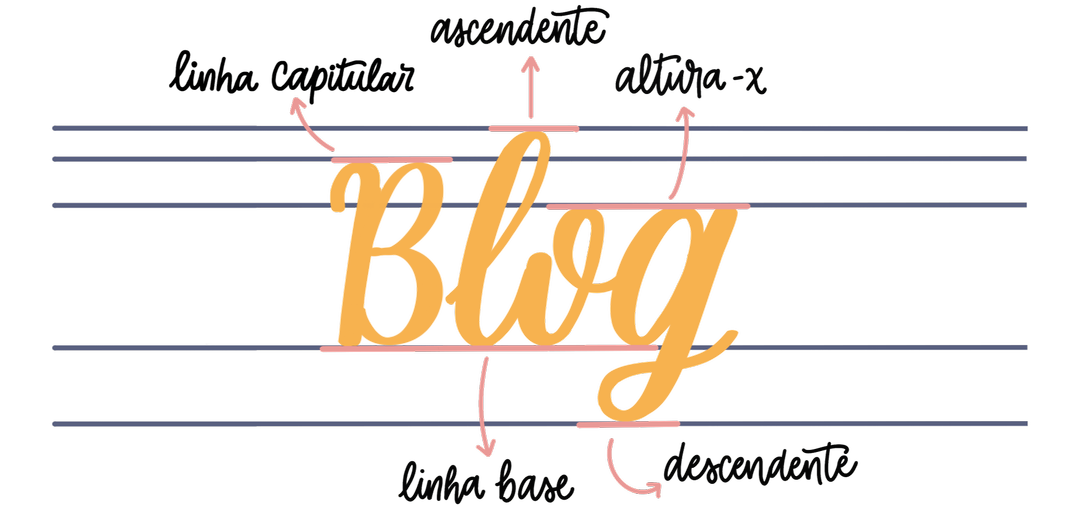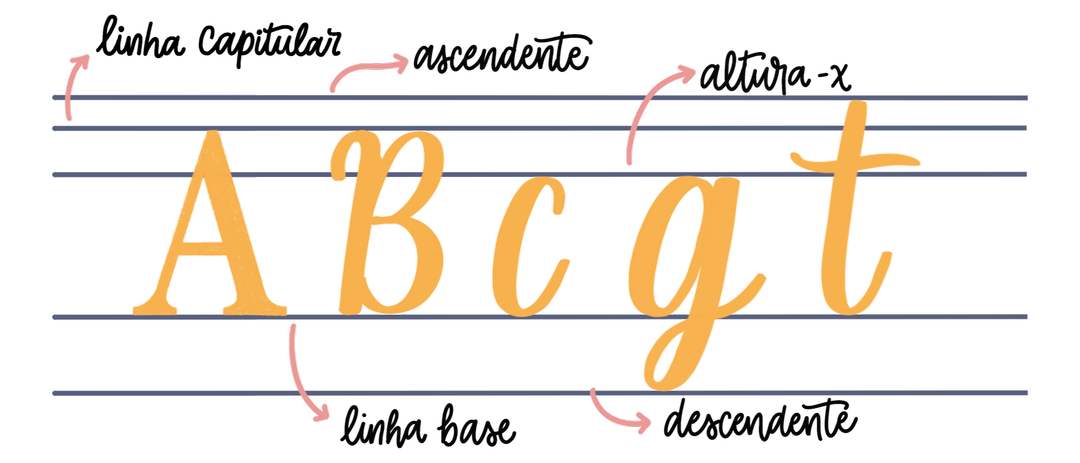
Linhas Guias
Nesse post vamos falar sobre as LINHAS GUIAS, o que são? Onde vivem? E como se alimentam? (brincadeira😅)
Vamos ver como você pode usá-las para melhorar as composições dos seus letterings.
As linhas guias são nossas melhores amigas quando estamos criando um lettering. Elas nos ajudam e nos guiam para manter todas as letras retas e alinhas entre si, e também a manter um padrão de altura em todas as letras de uma mesma palavra.
No total temos 6 linhas guias e agora vamos descobrir o nome delas:
Ascendente: É a linha que delimita a altura das letras cursivas minúsculas que tem um prolongamento para cima como por exemplo as letras: b, h, l, t, etc.
Linha das Capitulares: É a linha que demarca a altura das letras maiúsculas, ela é um pouco menor e fica logo abaixo da linha ascendente.
Altura x: É a altura das letras minúsculas como: a, c, e, o, i, m, n, etc.
Linha base: É a base onde as letras vão ficar “sentadas”, essa é a linha que faz com que as suas letras se mantenham retas e alinhadas.
E por último temos a linha descendente: É a linha que demarca até onde as letras minúsculas que tem um prolongamento para baixo descem, por exemplo: g, j, p e q, etc.
Linhas Guias na prática:
Analisando por exemplo a palavra Blog 👆 as linhas guias foram utilizadas da seguinte forma: a parte inferior das letras formam a linha base, enquanto a parte superior forma a altura-x.
Como a letra B é maiúscula ela se estende até a linha Capitular e parte inferior se mantem “sentada” na linha base.
A letra L, se estende acima da linha altura-x assim formando a linha ascendente. E a letra G se estende abaixo da linha base e forma a linha descendente.
Quais são as medidas das linhas guias?
Elas podem ter diferentes tamanhos, apenas diminuindo ou aumentando as medidas entre as linhas conseguimos ter letras com proporções e aparências diferentes, como você pode ver na foto abaixo, se as linhas estão mais próximas uma das outras ou seja, o "vão" entre elas é menor as letras ficam menores, já se estão mais longes as letras vão ficar mais altas e esticadas.
O tamanho de linhas guias que eu mais uso é aquela que o "vão" ou seja a distância entre a linha base e a altura-x é o dobro dos outros (a segunda na primeira fileira da foto acima), mas isso é apenas uma preferência minha, você pode testar todas elas e ver qual você gosta mais e se adapta melhor. Na foto você também encontra as medidas em cm que usei em cada uma delas.
E como elas podem ser usadas na hora de criar os letterings?
Como contei lá no inicio as linhas guias podem ser usadas para manter toda a composição reta, organizada, para que as palavras não fiquem muito próximas uma das outras e para que as letras se mantenham com um tamanho uniforme e alinhadas entre si.
Na imagem abaixo fiz um lettering representando o uso das linhas guias
Note que nas palavras "você" e "mesmo", usei apenas 2 linhas guias (linha base e altura-x), não precisei fazer a linha ascendente e nem a descendente, por que nessas 2 palavras não têm nenhuma letra que tem prolongamentos que passem da linha base ou da altura-x.
Um detalhe importante que quero destacar, as linhas guias devem sempre serem feitas a lápis com o uso de uma régua, logo nos primeiros passos da criação do lettering, comece pelas linhas guias e depois faça o desenho das letras, apague elas só depois de ter finalizado e passado a caneta no lettering.
E é isso, essas são as linhas guias, são bem simples de usar né?
Espero que este post tenha ajudado você a entender melhor sobre como elas podem nos ajudar principalmente quando estamos começando a criar nossos primeiros letterings. 🥰